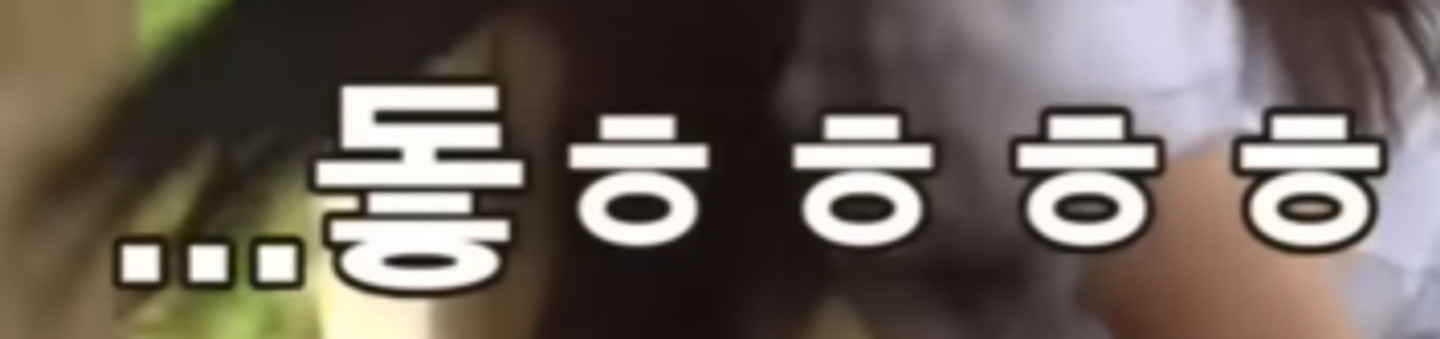
나영석 PD님 작품에서 많이 나오는 폰트인데 이름이 뭔가요? 디테일적인 부분에서 달라서 찾기가 어렵더라구요
DX새고딕
나PD 관련 예능에서는 '윤고딕' 계열 폰트가 나오는 경우가 있지만 이 폰트의 경우는 숫자가 확실히 윤고딕 계열이 아니므로 이 폰트가 사용된 듯합니다.
a견고딕